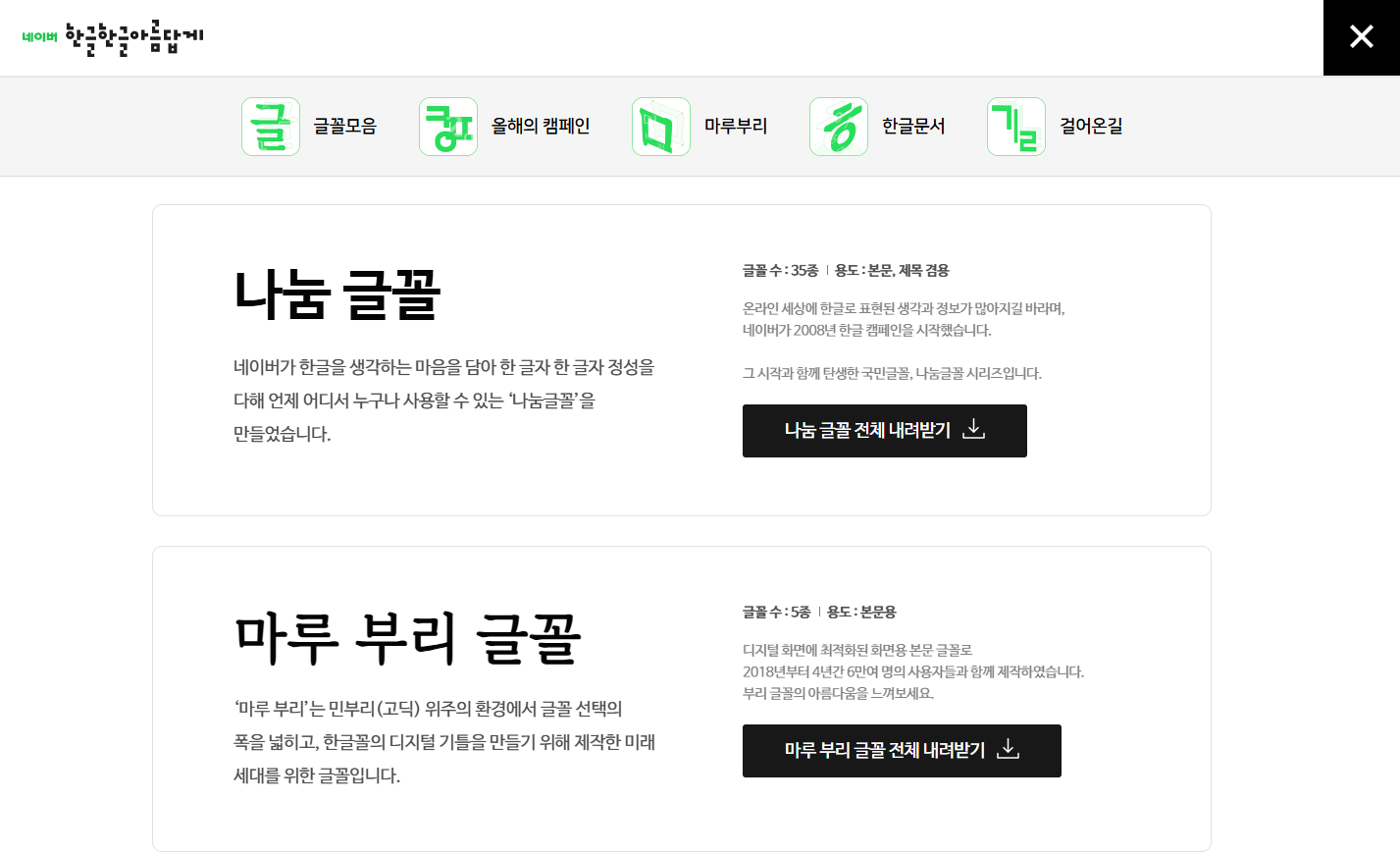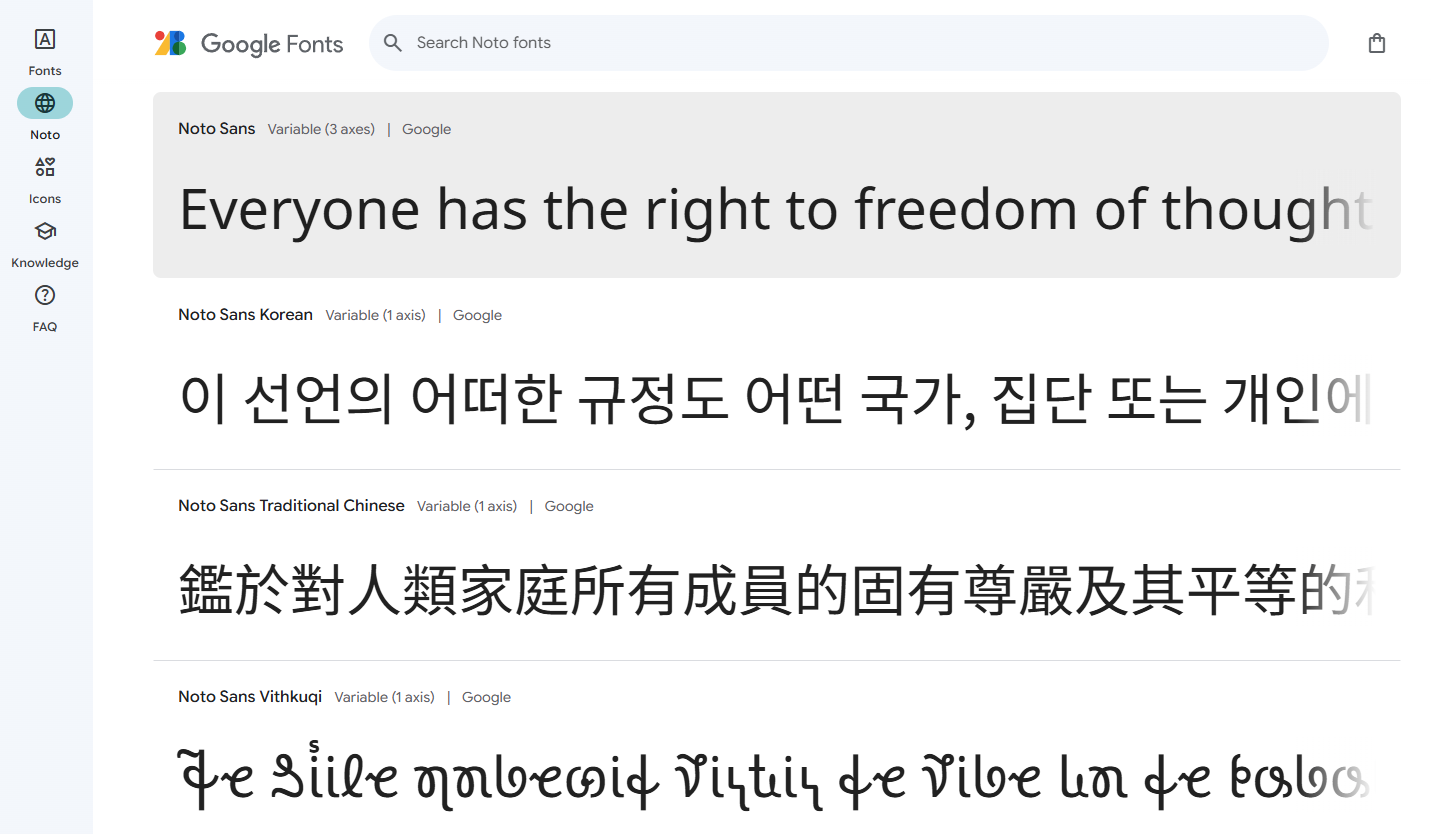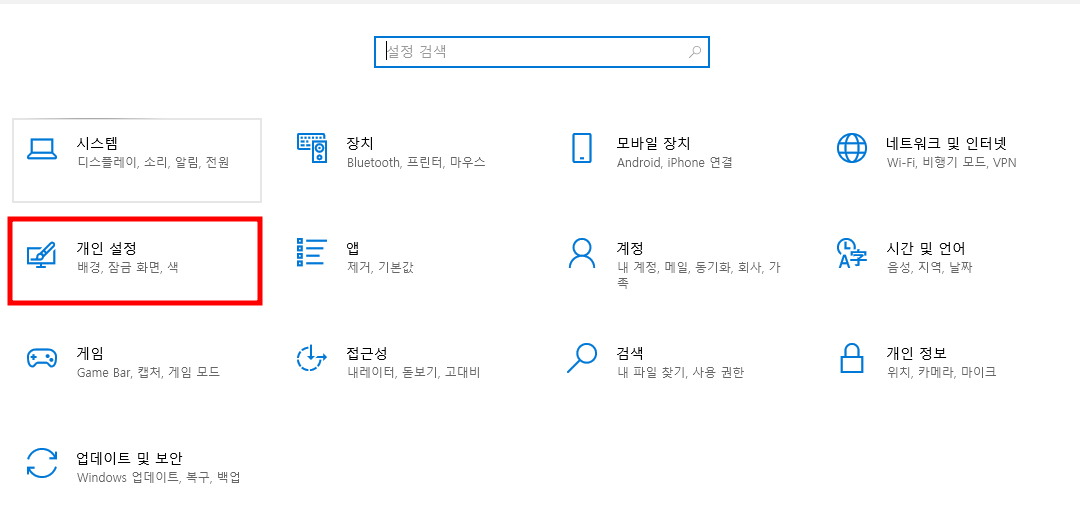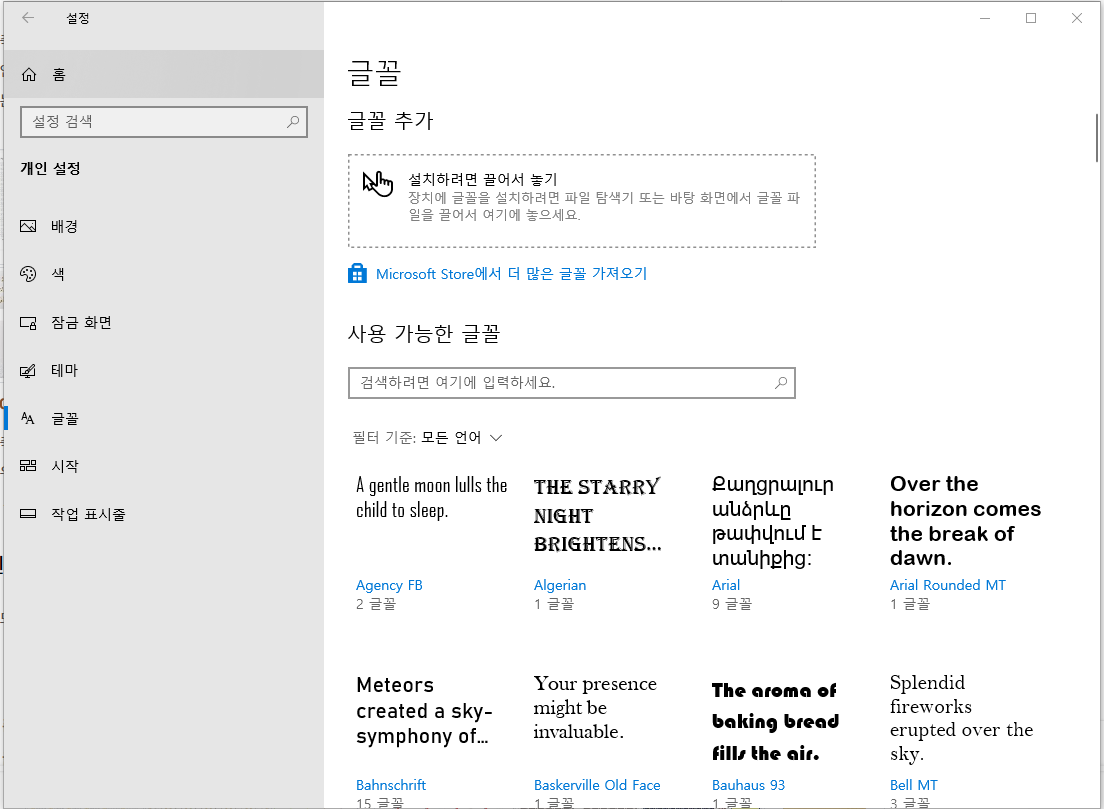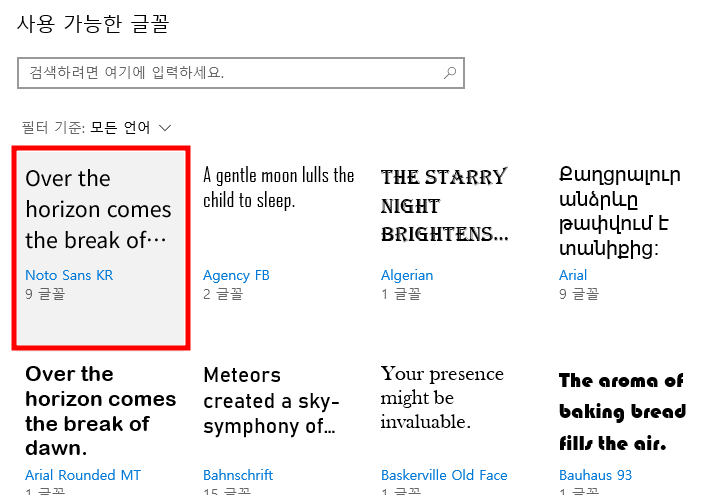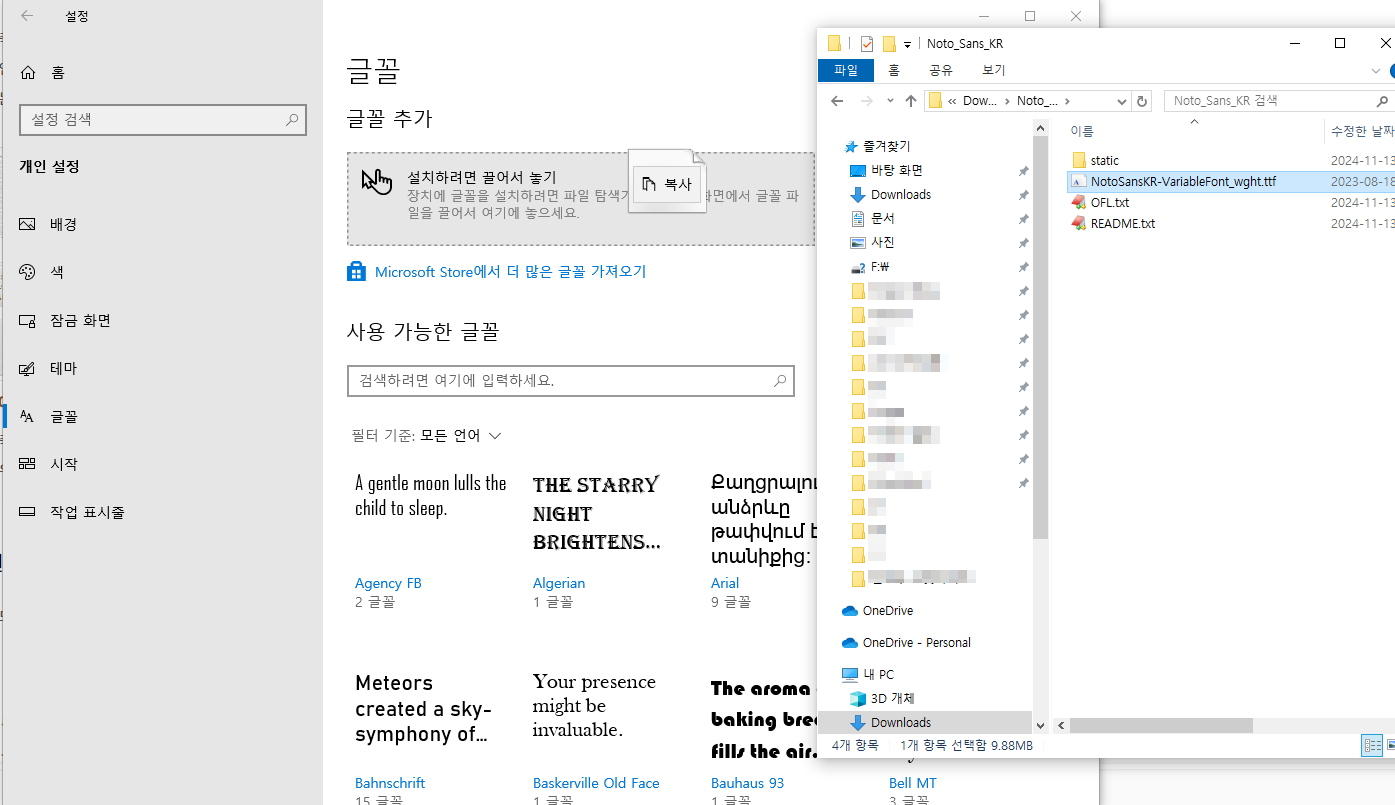
윈도우10 폰트 설치하는 방법 나눔글꼴, G마켓 산스
컴퓨터를 사용하다 보면 가끔 기본적으로 제공되는 폰트만으로는 부족하게 느껴질 때가 있습니다. 특히 문서 작업이나 블로그 작성, 디자인 작업 등을 할 때 원하는 스타일의 폰트를 사용하고 싶을 때가 있죠. 그런 경우 자신만의 독특한 글꼴을 설치해서 사용하면 작업의 완성도를 높이는 데 큰 도움이 됩니다. 또한, 더 나은 가독성과 독창적인 느낌을 주기 위해서라도 다양한 폰트를 사용하는 것이 중요합니다. 특히, 사용자가 특정 주제에 맞는 분위기를 표현하고 싶을 때 적절한 폰트를 사용하면 시각적으로 큰 차이를 만들 수 있습니다.
오늘은 윈도우10에서 쉽게 폰트를 설치하고 활용하는 방법을 소개해드리겠습니다. 이 과정은 크게 웹사이트에서 직접 다운로드하는 방법과 윈도우 설정을 통해 추가하는 두 가지 방법으로 나누어 설명하겠습니다. 이를 통해 보다 다양하고 아름다운 폰트를 자유롭게 설치하고 사용할 수 있는 능력을 갖추게 될 것입니다.
폰트 설치하는 방법 1: 웹사이트에서 직접 다운로드
특정 디자인을 위한 무료 폰트를 사용하고 싶다면 웹사이트에서 직접 다운로드하여 설치할 수도 있습니다. 이 방법은 조금 더 복잡할 수 있지만, 다양한 선택지를 제공합니다. 인터넷에는 수많은 무료 폰트들이 존재하며, 이를 통해 사용자는 자신만의 개성을 표현할 수 있습니다.
- 폰트 다운로드
네이버나 구글에서 '무료 폰트 다운로드'를 검색하면 다양한 사이트에서 제공하는 무료 폰트를 찾을 수 있습니다. 대표적으로 '네이버 나눔글꼴', '다음체', '구글 폰트(Google Fonts)' 등이 있습니다. 이러한 사이트에서는 무료 폰트뿐만 아니라 상업적으로도 사용 가능한 폰트들을 제공하여, 필요한 경우 라이선스를 확인한 후 자유롭게 사용할 수 있습니다. 또한, 이러한 무료 폰트들은 다양한 디자인 스타일을 갖추고 있어 특정 프로젝트의 필요에 따라 선택할 수 있는 폭이 넓습니다.
- 다운로드한 파일 압축 해제
대부분의 폰트는 .zip 파일로 압축되어 제공됩니다. 압축을 해제한 후, .ttf(TureType Font) 또는 .otf(OpenType Font) 파일을 확인하세요. 이 과정에서 압축 해제 프로그램이 필요할 수 있으며, 윈도우에는 기본적으로 압축 파일을 해제할 수 있는 기능이 포함되어 있습니다. 폰트 파일을 잘못된 위치에 저장하지 않도록 주의해야 하며, 폰트 파일을 한 곳에 모아 정리해 두면 나중에 관리하기가 용이합니다. - 폰트 설치하기
압축을 해제한 폰트 파일(.ttf 또는 .otf)을 마우스 오른쪽 클릭한 후 '설치'를 선택하면 설치가 완료됩니다. 이때 '관리자 권한'이 필요할 수 있으니, 해당 창이 나타날 경우 '예'를 클릭해 주세요. 설치 후에는 폰트가 시스템에 적용되어 모든 프로그램에서 사용할 수 있게 됩니다. 설치한 폰트는 워드, 엑셀, 파워포인트 등 다양한 프로그램에서 바로 사용할 수 있어 작업의 퀄리티를 높이는 데 유용합니다.
폰트 설치하는 방법 2: 윈도우 설정을 통한 폰트 추가
윈도우 설정을 통해서 폰트를 추가하는 방법도 있습니다. 이 방법은 다운로드한 폰트를 드래그 앤 드롭 방식으로 쉽게 설치할 수 있어 매우 간편합니다. 특히 다수의 폰트를 동시에 설치하려 할 때 유용합니다. 폰트를 추가적으로 설치함으로써, 사용자 인터페이스의 개인화가 쉬워지고, 작업 시 더욱 편리한 환경을 만들 수 있습니다.
- 설정 열기
'시작 메뉴'를 클릭하고 '설정'을 검색하여 열어주세요. 설정 메뉴는 윈도우의 주요 기능을 제어할 수 있는 곳으로, 사용자 환경을 손쉽게 조정할 수 있습니다. 이러한 설정을 통해 사용자 경험을 향상시킬 수 있습니다. 윈도우 설정 메뉴에서 폰트를 설치하는 과정은 사용자 친화적인 UI를 제공하여 누구나 쉽게 따라 할 수 있습니다. - 개인 설정 > 글꼴
- 드래그 앤 드롭 설치
폰트를 설치하려면 다운로드한 폰트 파일(.ttf, .otf)을 이 폰트 창으로 끌어다 놓으면 자동으로 설치가 진행됩니다. 드래그 앤 드롭 방식으로 파일을 옮기기만 하면 되기 때문에 매우 편리하며, 초보자도 쉽게 사용할 수 있는 방법입니다. 특히 여러 개의 폰트를 한꺼번에 설치할 수 있어, 작업 시간 단축에도 도움이 됩니다. 설치한 폰트는 시스템 전반에 적용되기 때문에 엑셀, 워드, 파워포인트 등에서 자유롭게 사용할 수 있습니다.
폰트 관리 방법
폰트를 많이 설치하면 컴퓨터 속도에 영향을 미칠 수 있기 때문에 꼭 필요한 폰트만 설치하는 것이 좋습니다. 이미 설치한 폰트를 관리하려면 '설정 > 개인 설정 > 폰트'에서 설치된 폰트 목록을 확인하고 삭제할 수 있습니다. 특정 폰트가 더 이상 필요 없을 경우, 해당 폰트를 클릭하고 '제거' 버튼을 눌러 삭제할 수 있습니다. 이렇게 하면 시스템 자원을 절약할 수 있고, 컴퓨터 성능 저하를 방지할 수 있습니다.
폰트 관리는 문서 작업의 효율성을 높이기 위해서도 중요합니다. 특히 디자인 프로젝트에서는 필요 없는 폰트를 정리해 두는 것이 중요하며, 자주 사용하는 폰트만을 관리하는 것이 작업 속도를 높이는 데 유리합니다. 예를 들어, 디자인 작업에서 불필요하게 많은 폰트가 설치되어 있으면 폰트를 선택하는 데 시간이 걸릴 수 있습니다. 이를 방지하기 위해 폰트를 주기적으로 관리하고 정리하는 것이 좋습니다.
추천하는 무료 폰트
- 네이버 나눔글꼴: 깔끔하고 기본적인 느낌의 글꼴로, 다양한 굵기와 스타일이 제공되어 문서 작업에 유용합니다. 네이버에서 제공하는 이 폰트는 상업적 용도로도 사용이 가능하여 인기가 많습니다. 또한, 다양한 굵기를 통해 다양한 용도로 활용할 수 있으며, 개인 블로그부터 상업적 프레젠테이션까지 폭넓게 사용됩니다.
- 에스코어 드림: 현대적인 느낌의 폰트로, 두께가 다양하여 상황에 맞게 사용할 수 있습니다. 디자인 작업에 특히 잘 어울리며, 다양한 굵기를 활용하여 시각적 강조를 줄 수 있습니다. 시원하고 깔끔한 느낌을 주어, 광고물이나 포스터 제작에도 유용합니다.
- G마켓 산스: 심플하면서도 강렬한 느낌을 주는 폰트로, 타이틀이나 헤드라인에 사용하기 좋습니다. 개인적으로 G마켓 산스는 심플하면서도 강렬한 느낌 때문에 특히 선호하는 폰트입니다. 구글 독스나 프레젠테이션 작업에도 잘 어울리며, 사용 후기가 매우 긍정적입니다. 다양한 디자인 작업에서 활용할 수 있으며, 굵기 변화가 다양한 점이 매력적입니다.
- 카페24 써라운드: 귀엽고 아기자기한 느낌을 주며, 개인적인 블로그나 아동 관련 콘텐츠에 적합합니다. 이 폰트는 손글씨 느낌이 강하여 친근하고 부드러운 이미지를 줍니다. 특히 동화책이나 어린이용 자료 제작에 매우 잘 어울리며, 따뜻한 분위기를 강조할 때 사용하기 좋습니다.
- 프리텐다드: 간결하고 세련된 느낌의 폰트로, 다양한 굵기로 제공되어 디자인 프로젝트에서 효과적으로 사용할 수 있습니다. 가독성이 뛰어나 프레젠테이션이나 보고서에서도 유용합니다. 또한, 고급스러운 느낌을 주기 때문에 브랜드 로고나 고급 제품의 패키지 디자인에서도 적절하게 사용할 수 있습니다.
- IBM Flex Sans Kr: PDF로 저장해도 일관된 품질을 유지하며, 미려한 디자인으로 많은 사용자가 선호하는 폰트입니다. 구글 독스 및 프레젠테이션에서 특히 효과적입니다. 가독성이 우수하여 긴 문서에서도 눈의 피로를 줄여줍니다. 명확하고 깔끔한 인상을 주며, 공식적인 문서에서도 많이 사용됩니다.
- 페이퍼로지 폰트: 한글은 G마켓 산스를, 영문은 Montserrat를 결합하여 만든 폰트로, 굵기가 9개로 제공되어 다양한 활용이 가능합니다. 상업적 사용도 가능하며, 다운로드 링크는 노누 폰트 사이트에서 가능합니다. 각기 다른 굵기 덕분에 여러 종류의 문서에서 유연하게 사용 가능합니다. 특히 광고 디자인이나 프레젠테이션 타이틀에서 매력적인 조합을 보여줍니다.
- D2Coding: 개발자용으로 매우 인기 있는 폰트로, 특히 D2Coding의 ligature 기능을 좋아하는 사용자가 많습니다. Putty와 같은 터미널 프로그램에서도 기본 폰트로 많이 사용됩니다. 프로그래밍을 하는 사용자에게는 매우 편리하며, 코드 가독성을 높이는 데 도움이 됩니다. 이러한 점은 디버깅이나 긴 코드 작업에서 특히 유리합니다.
- Jetbrains Mono: 코딩 작업에 적합하며, fallback 폰트로 D2Coding을 설정하여도 잘 어울립니다. 이 폰트는 코드 작성 시 눈의 피로를 덜어주며, 프로그래밍 언어의 가독성을 높여줍니다. 특히, 프로그래머들이 선호하는 폰트로서 복잡한 코드 구조도 명확하게 볼 수 있게 해 줍니다.
- 노토 산스: 기본적인 가독성이 뛰어나며, 브라우저 글꼴로도 많이 사용됩니다. 특히 네이버 나눔스퀘어 네오로 설정하면 가독성이 매우 향상됩니다. 이 폰트는 특히 웹페이지에서 텍스트가 많은 경우 유용하며, 다양한 상황에서 활용 가능합니다. 웹디자인 작업이나 모바일 앱에서 사용하면 일관된 느낌을 줄 수 있습니다.